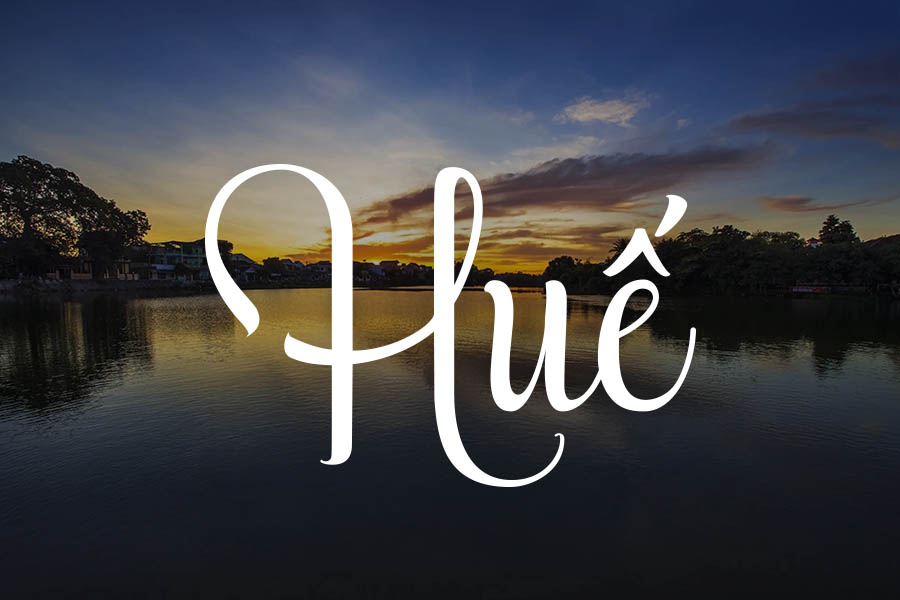
Tác giả Mats-Peter Forss
SVN-Amethyst là một font chữ viết tay Việt hóa cao cấp, nổi bật với nét chữ mềm mại, uyển chuyển và đầy tinh tế. Được Việt hóa bởi SVN Fonts, font mang đến trải nghiệm thiết kế chuyên nghiệp nhờ hệ thống ký tự hỗ trợ tiếng Việt đầy đủ và sắc nét.
Phong cách của font SVN-Amethyst mang hơi hướng nữ tính, thanh lịch và có độ bay bổng nhẹ nhàng. Font đi kèm với nhiều ligaturesalternates, cho phép người dùng linh hoạt sáng tạo trong các dự án như: thiết kế logo thương hiệu mỹ phẩm, thiệp cưới, bao bì sản phẩm handmade, typography nghệ thuật, hoặc blog cá nhân mang phong cách nhẹ nhàng.
Nếu bạn đang tìm kiếm một font chữ viết tay thanh lịch và chuẩn tiếng Việt, thì SVN-Amethyst Việt hóa chính là lựa chọn hoàn hảo để tạo nên những thiết kế sang trọng, cuốn hút và đầy cảm xúc.